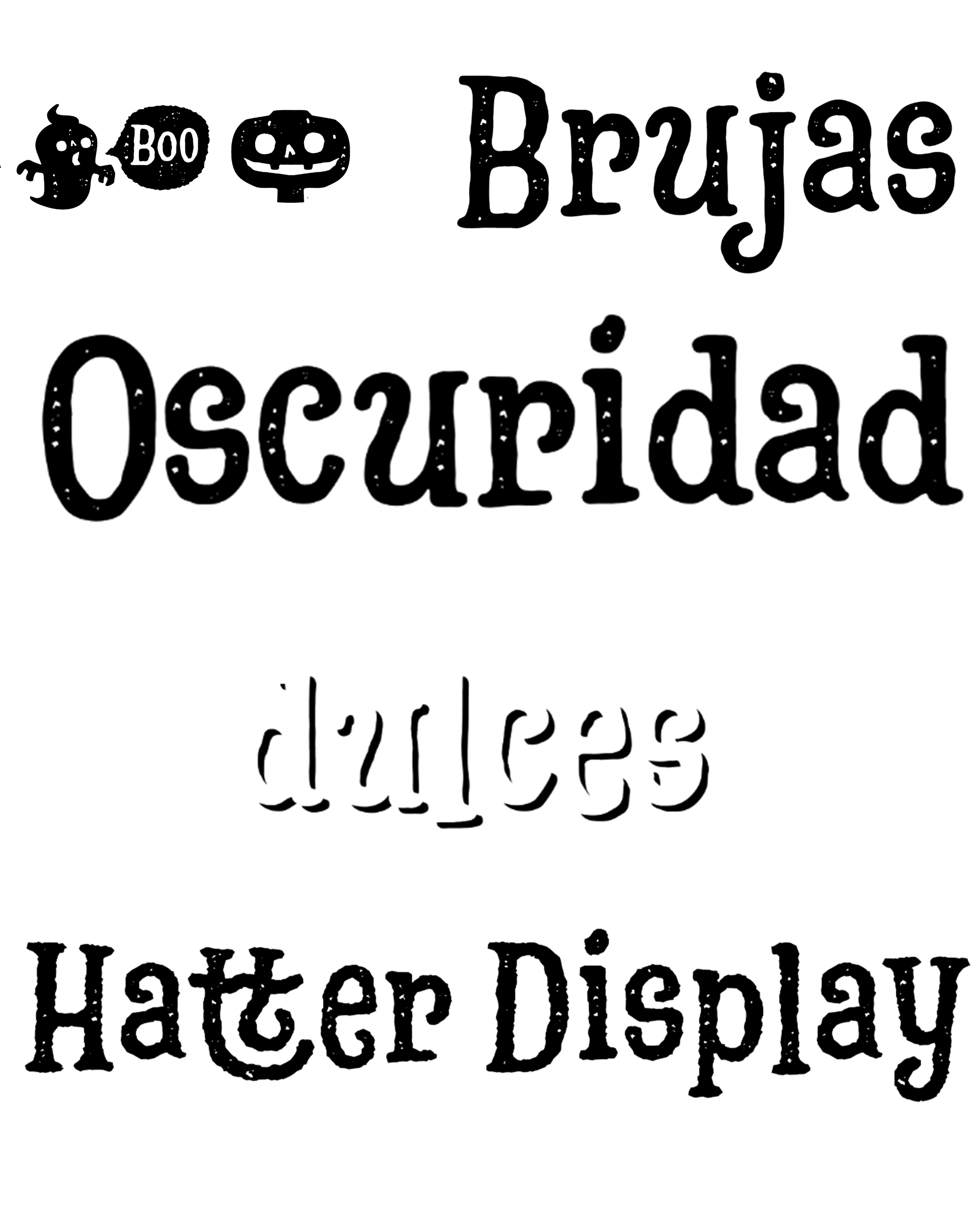
Hatter Display Pro
| Descripción | La familia tipográfica Hatter Display Pro fue diseñada por Rodrigo Araya Salas y publicada por RodrigoTypo. Hatter Display Pro contiene 12 estilos y opciones de paquete familiar. Esta es la versión más completa y final de Hatter, contiene más de 12 fuentes, entre ellas contiene Cyrillic, Swash, Alternatives, Dingbats, Ornaments, todo para hacer un gráfico entretenido. |
| Clasificación | Títulos, Experimental, Dingbats |
| Familia(s) | Hatter Display Pro Regular, Hatter Display Pro Dirt, Hatter Display Pro Dirt Two, Hatter Display Pro Shadow, , Hatter Display Pro Ornament Dirt, Hatter Display Pro Ornament Line, Hatter Display Pro Ornament Only Line, Hatter Display Pro Dingbats, Hatter Display Pro Dingbat Dirt |
| Estilos | 12 |